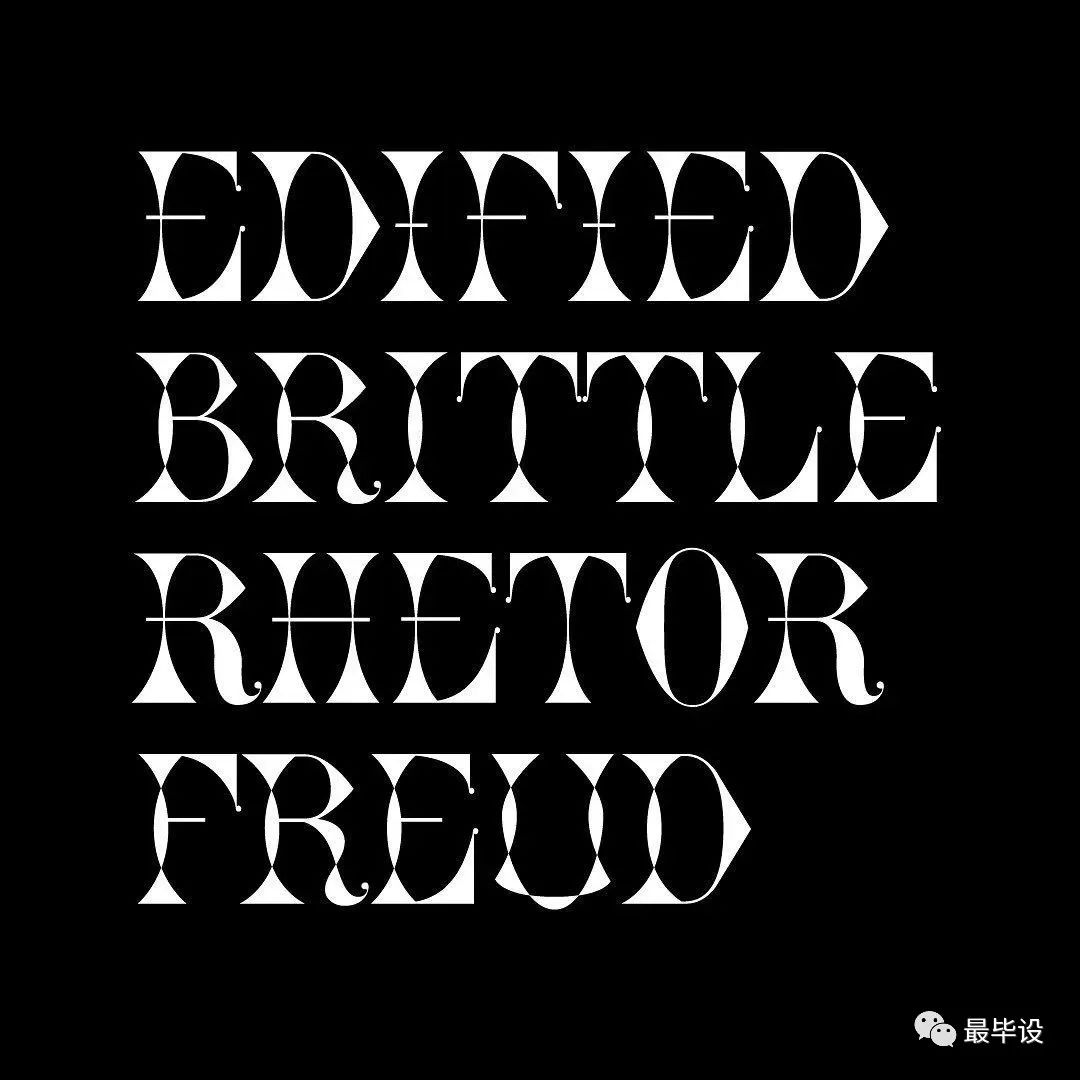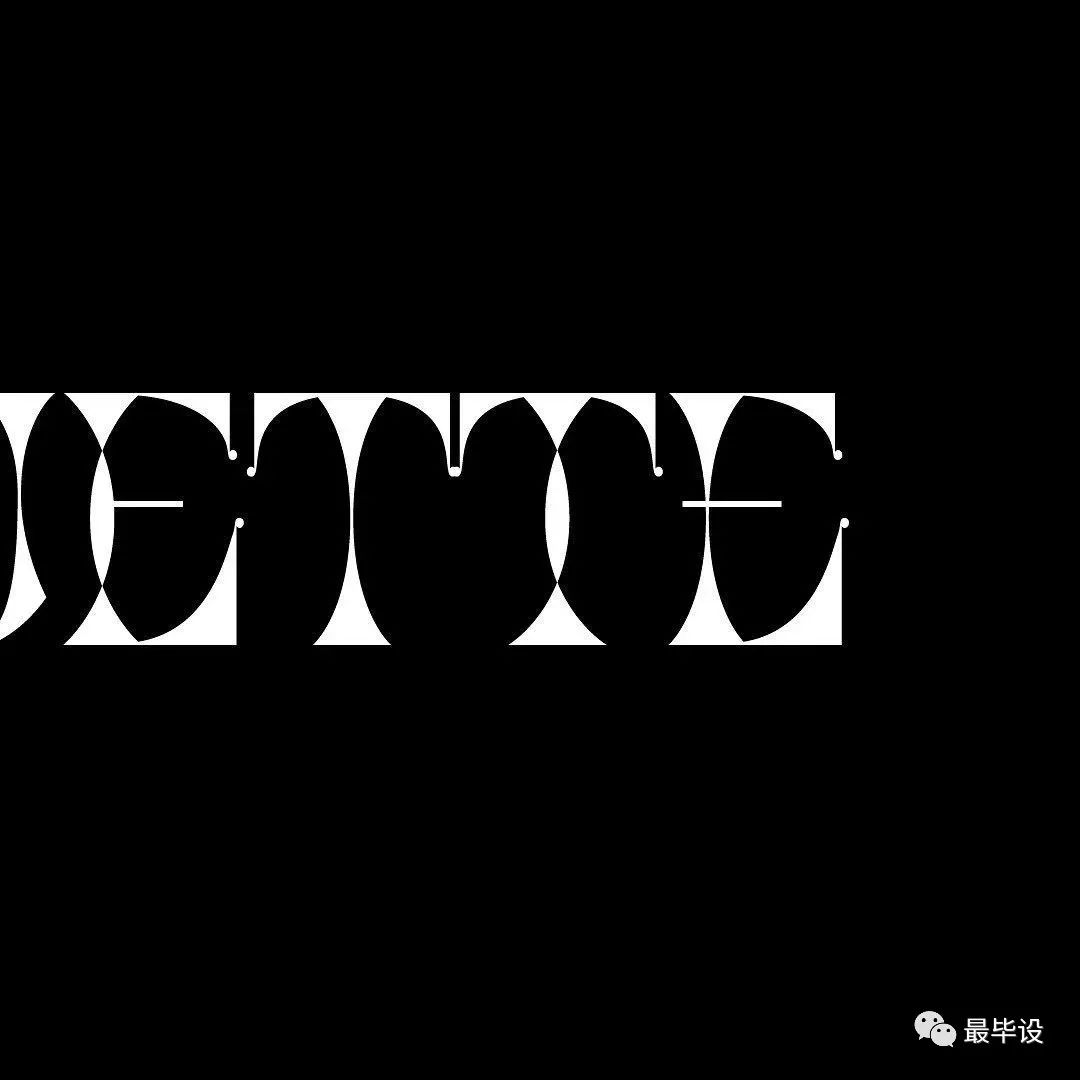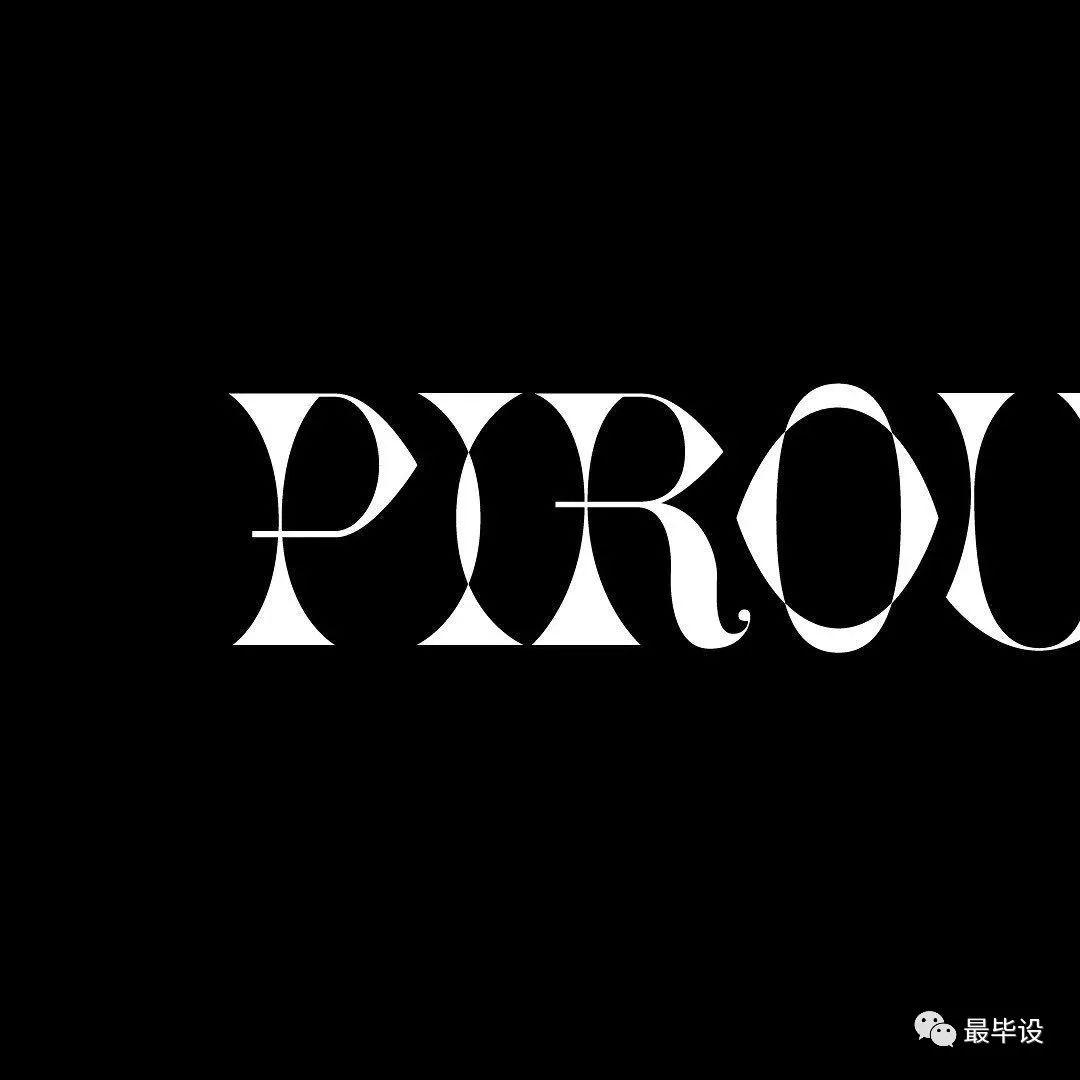
全美Top3 MICA 平面毕设玩出新花样!
本期文章,我们来到 —— MICA 马里兰艺术学院。
为了应对未来市场的变化,MICA 平面设计系鼓励学生进行跨学科研究,选修数字媒体、社交媒体、视频和电影制作等课程,旨在培养学生制作跨媒体的复杂项目。所以在每年的毕业展中,总会看到各种有意思的表达形式。
今天,为大家带来 MICA 平面设计研究生的 19 个毕设。
今年毕设主视觉
——
“未来是交互的”
AR 交互 / 虚拟媒介
1. 3D 光学字母 | 一场 VR+AR 实验
THE FIFTH MEDIUM  第五媒介
作者:Cmo Yu
关键词:多维度媒介、虚拟现实、3D光学字母、VR / AR实验
该作品通过探索多维度媒介(二维,三位, 四维,虚拟现实和现实增强)的不同方式来展示一组光学字母。
Cmo 认为,这五种媒介都有自己的优缺点,并且带给人的体验各不相同,因此各个媒介之间都是平等的。她认为,在不久的将来“屏幕”这一概念将会被增强普及。这种可以从不同角度观察到的3D字母的形式,也将成为研究和使用的新兴领域。
这种形式可以使用VR耳机进行体验以及可以由智能设备(unity+ vuforia)进行 AR 打印。
· 嵌入式360 视频 VR
· 关于增强现实
· 印刷文字银河
2. 感受与时间的交互
A Matter of Time
作者:Ella Huang
关键词:时间、静物、交互
A matter of time 是一个 3D 打印雕塑和延时视频相结合的交互体验设计。作者选取了五个静物:苹果、花、蜡烛、水和石头并用不同的方式使用它们来体验时间。
当观众持续触摸每个物品时,界面会伴随着一段属于这个物件独特的声音,以展示这个物品是如何记录和经历属于它的时间这一过程。
在这个项目里,它们代表的是不规则(特殊)的时间记录者,时间的感受存在于我们自己的意识里。
每一位参与交互的观众都是比石头时间幅度短而比其他物件时间幅度长的第六个时间体验和记录者。每件物品以不同的方式离开我们的生活,它们不仅是时间的记录者,也是时间的体验者。
3. AR 带你进入一场拉丁童话
Mountain Mother & Other Stories 讲述拉丁文化故事
作者:Katty Huertas
关键词:童话 文化 故事叙述
Mountain Mother & Other Stories 是一个使用了多种视觉方式来讲述传统拉丁文化故事的设计项目。通过插画、设计师撰写故事、字体设计、手工书和雕塑装置等方式,建立了 Mountain Mother 这个故事并用 AR 现实增强技术 来动态呈现了 Mountain Mother 这个人物所处的童话世界。
4. 3D 动画探索人类满足感
Biophilia
作者:Sean Dong
关键词:3D 动画、ASMR
Biophilia 是对于一场满足感的视觉探索。作者通过动画展示了人类对于物体在世界中本该存在的样子,通过 3D 和声音的结合,作者制作了一系列舒适小动画来传达这一感受。
Sean 通过使用循环播放 3D 动画和 ASMR 声音,来优化感官体验。“ Biophilia 这个作品是以我将周围世界的美好回忆的收集为特色,通过动画来使人们感到满足。” Sean 如是说。
5. 电子虚拟墓场
DEPARTMENT OF DIGITAL REMAINS (电子遗留部门)
作者:Anjaloi Nair
关键词:虚拟平台
在 2050 年,Facebook 上死亡的人数会超过生存的人数,那时这个平台将会变成一个虚拟的墓场。
在这个不朽的电子时代,这个设计项目是一个推测我们的虚拟身份在我们去世之后。电子遗留部门是一个虚拟的联邦部门,会帮助我们记录所有的虚拟操作。你在去世后在虚拟平台上的位置取决于你活着的时候。
6. 互动滤镜探究你的舒适尺度
Boundaries of Comfort (舒适的尺度)
作者:Min Li
关键词:互动滤镜
用可互动的滤镜来探究人们对于裸体的舒适尺度。裸体的模糊滤镜会随人的移动距离而改变,因此对于审查的尺度取决于观众的距离。
7. 交互连接音乐和字体
The Acoustics of Typography
作者:Vivek Thakker
关键词:声学、交互
声学文字是用理论与实践结合的方式来探索字体排印和音乐的情感连接。追寻其对于沟通的深层次理解,这个项目从复杂的情感出发,通过生成和交互技术来展现其之间的相通性。
——
字体设计的多元化
8. 可变字体,探索女权意味着什么
Nari Variable // Nari  可变字体
作者:Aasawari Kulkarni
关键词:女权、可变字体
Nari Variable 是一组传达女权主义信息的反父权制海报。作者以流畅、富有表现力和诗意的方式对可变字体进行了探索。
作者还设计了一系列明信片,明信片上的信息来自对2019年9月进行的印度妇女调查的回应。这些都是真实女性的真实故事,在印度做一名女性通常与西方大不相同。Aasawari 希望人们通过这个作品能对其能有更多的理解。
9. 字体“加工厂”推翻传统字体设计
EXTRA BOLD ITALIC FOUNDRY // 加粗斜体工厂
作者:Shivani Parasnis
关键词:字体设计
这个设计项目从展示字体的角度出发,作者设计了四套展示字体,并将通过展示不同寻常,意想不到的字母来推翻传统。这四套字体旨在创建有关当前显示字体概念的论述,并为字体设计者提供替代观点。
10. 不同国家的人公同创造汉字
GATHER 聚集
作者:Xiaoyu Song
关键词:字体设计、汉字拆解
汉字是通过将不同的简单元素的组合到一起来传达复杂的含义。作品通过拆分笔画,然后邀请不同国家的参与者用汉字笔画组成不同国家的文字。
赵孟頫《汉汲黯传》
该项目启发于留学生群体希望通过文字能够带给大家“归属感”从而消除孤独感。单独的中文笔画只是一个图形,多个笔画组成在一起才能够形成充满着多种意义的文字。基于中文楷体设计的衬线笔画更具书法风格以及更加符合现代数字时代的无衬线笔画。从而在时间上表明了人类交流的变化从手写书信到打字。
——
社会现象 / 文化传承
的多种视觉呈现
11. 平面设计如何诠释文化冲突
Hybridentity 双重文化
作者:Ning Chen
关键词:文化传承、China Town
Hybridentity 是通过语⾔的融合和冲突来表现中美文化杂糅现象的一个探索,用不同材料的标牌作为媒介,展示了中美文化杂糅现象所带来的一种超现实主义的、模棱两可的感受和体验。
作者希望观众可以对标牌背后的意义以及中美两种文化之间的关系产⽣思考。
在调研过程中,Ning 发现了霍⽶巴巴( Homi K. Bhabha ) 的文化杂糅理论学说 ( Cultural Hybrid )。文化不是一个完美的融合体,而是一个由其他文化构成,并相互作用的混合体。这也同样适⽤于曼哈顿唐⼈街现象。
12. 男人就是要粉红色
Cis-sy
作者:Yash Goel
Web:https://www.yash-goel.com/
关键词:Gender & Sexuality 性别探索
这个项目是对男子气概和性别的探索与表达。
Yash 试图挑战传统对于男子气概的认知,同时也不断的挖掘这一概念对于自己的影响。通过这个项目的一系列探索,作者想表达的是性别不是从出生的那一刻就决定的,而是你自己来定义。
这个作品是一项摄影、出版物设计、装置设计和纺织品生产的结合体,所有的这一切都是在宣扬“ You do you ”。
是谁规定的男人不适合粉色,男人不允许哭?
13. 一个虚拟设计练习
The Slug and The Minion
作者:Lindy Zhu
Web: https://www.behance.net/lindyz
关键词:构建世界,迭代设计,环境
要完成一个设计项目,有的人会直接从目标出发来指导实践,还有的人会先探索和修正不 同的可能性来趋近目标。
The Slug and The Minion 运用了游戏领域常使用的先建构世界/ 再讲故事的方法来指导设计,世界中的两个主要角色分别代表了人类和自然,聚焦当下环 境污染的议题。
构建世界来趋近表达目标就是不停地纠正和迭代设计中产生的逻辑矛盾,中间很多时间是用于 写设定/改设定/调整视觉构图的过程。
一张中期的概念图,当时是想设计造成水和气体双重污染的能源,工厂的母体/子体。
玻璃小人儿气体加工厂
玻璃小人儿和鼻涕虫君的故事板
现实工厂、海报和玻璃杯小人儿
14. 一个专供拉丁设计师的网站
作者:Zuli Segura
Web:http://latinxdesigndirectory.com/
关键词:拉丁文化
拉丁文化设计录是一个拉丁裔设计师的开放平台,网站展示了当下活跃的拉丁设计师并且作为一个平台让更多人看到这些设计师。这个平台也为设计师提供更多的交流和沟通的机会,让更多人参与到其中。
15. 一个能帮助青少年身心健康的工具盒
The Den
作者:Ashley Fletcher
Web:ashley-fletcher.com
关键词:青少年健康
The Den 是一个健康项目,通过日常的活动和射击游戏来帮助10-14岁间的非裔美籍青少年提高身心。作者设计了一个工具盒,其中会有活动指导及相关的内容来帮助青少年学习合作。
——
灵感来源
可以是你的喜好
也可以是你的生活
16. 家族史也能成为灵感来源
ANTHROPO — SCENES(人类纪元)
作者:Cora McKenzie
Web:coramckenzie.com
关键词:环境、气候、家族调研
“人类纪元”通过一系列的设计实验,来挖掘人类物种对于地球的影响,通过 过去、现在、未来 的时间视角以平面设计的方式,帮助我们观察这个时代。
有生物学专业背景的 Cora 首先对环境的变化做了调研,她汇集了因人类行为而引起的环境变化事件,并且为了观察大众的舆论,她整理人们在推特上对 #人类世# 话题的讨论。
最后,Cora 以 未来、现在、过去 为概念主题,用三种表现方式来呈现本次的研究。分别是:以未来视角,设计一套视觉语言、为过去设计悼念首饰;为现在举办一次展览,汇集推特上人们的舆论。
17. 喜欢跳 Breaking 能为我的设计做些什么
EXTEND THE CYPHER 街舞文化
作者:Gregory Fisk
Web:www.fisk.studio
关键词:街舞、档案
Gregory 是一个街舞爱好者,他通过调研街舞的历史,设计实验,交互和整理文档的手段来展现街舞 Breaking 文化。这套视觉系统旨在共享知识和保存历史,同时揭示如何以真实的观点进行设计实践。
Gregory 从字体排印开始制作了一系列的海报,确定了相应的视觉系统不如颜色、字体及形式,后期将海报扫描复制肌理和字体将其做成动态海报。之后又制作了网站来收集街舞的历史资料与录像作为开放资源。
从兴趣点出发其实是一个很好的切入手段,我们总说毕设虽然很重要但其实它更多的是一个挖掘和整理的过程。通过这个作品将自己的喜好整理出来让更多的人看到,这也不失为一件很有意义的事。
18. 情绪动态海报
NEW COMPOSITION 新构成
作者:James Marshall
Web:http://www.jamesmarshall.online/
关键词:动态海报、情绪海报
新构成,是通过海报的形式对于动态与感知的探索。以焦虑为出发点,设计师创造了一系列可以展示动态海报的投影装置。
设计的初衷是探索动态海报的更多展示可能性,但在设计的过程中作者更多地将情绪融入到设计当中,并制作了一系列的情绪动态海报。
19. 将信息整合能力诠释成作品
Reframe 重新定义
作者:Congjia Jin
关键词:mapping、思维导图
RE{FRAME} 是以个人经历为主线来探索不同设计思维与方法的项目。在设计探索过程中, 将学到、观察到的事物与思考方式进行整理归纳,总结成为自己的设计方法,作者将整个过程称为 RE{FRAME} 重新定义。
每个人对于事物的诠释方式基于自己的经历经验和文化背景各不相同,因为 Congjia 发现自己对于大量信息的整理与整合有很大的兴趣,因此,在此基础上她通过 mapping 也就是各种制图的方式来探讨了这一话题。